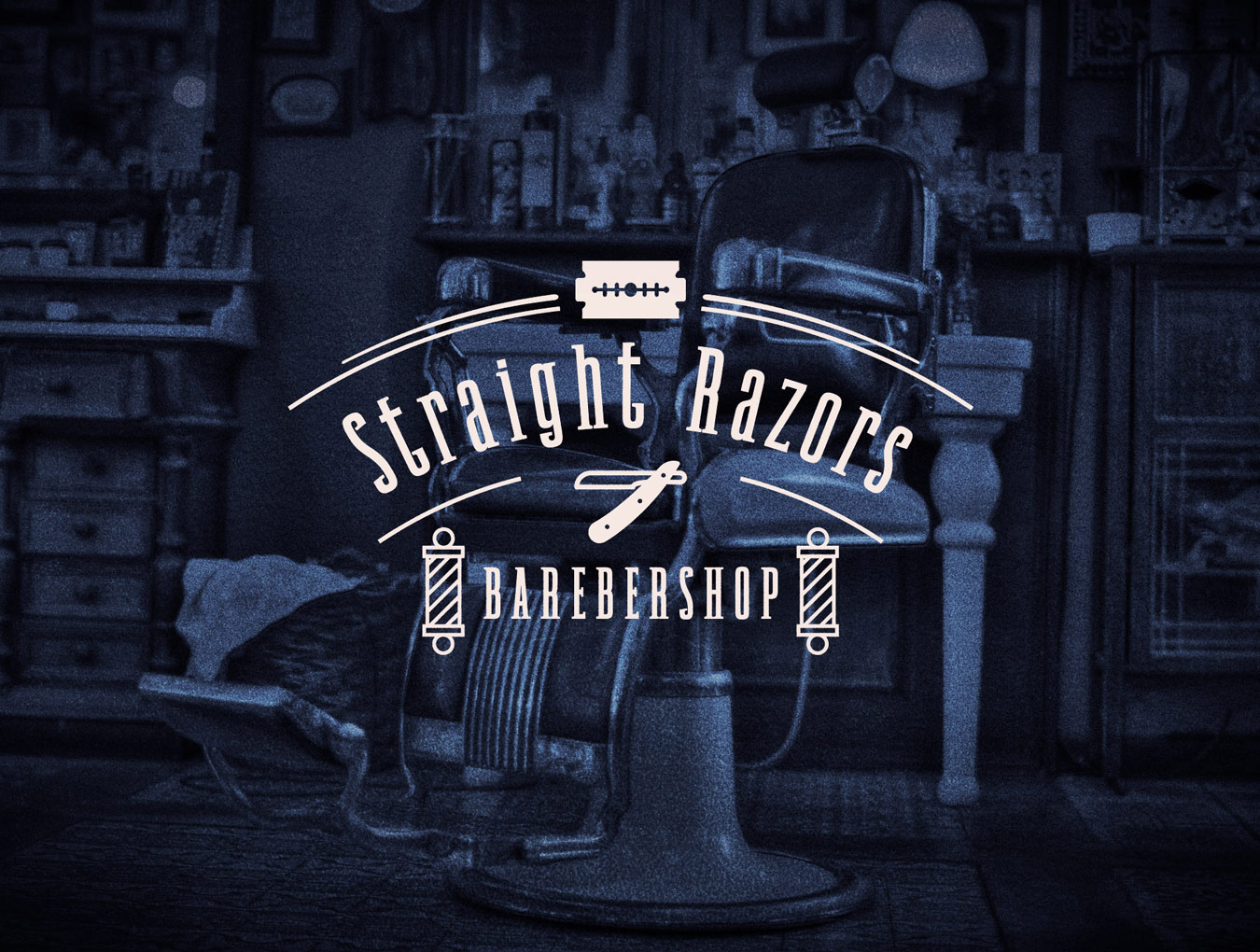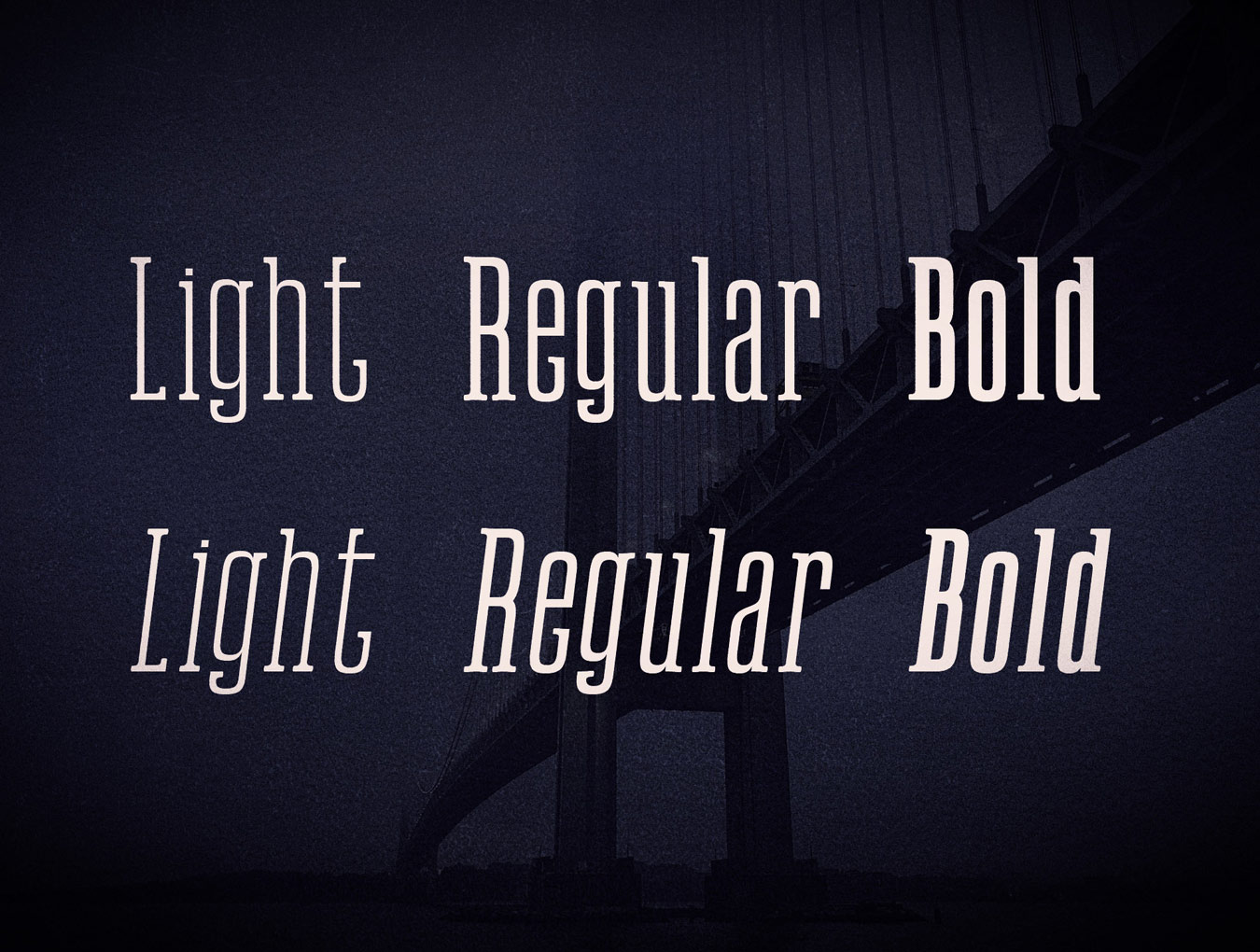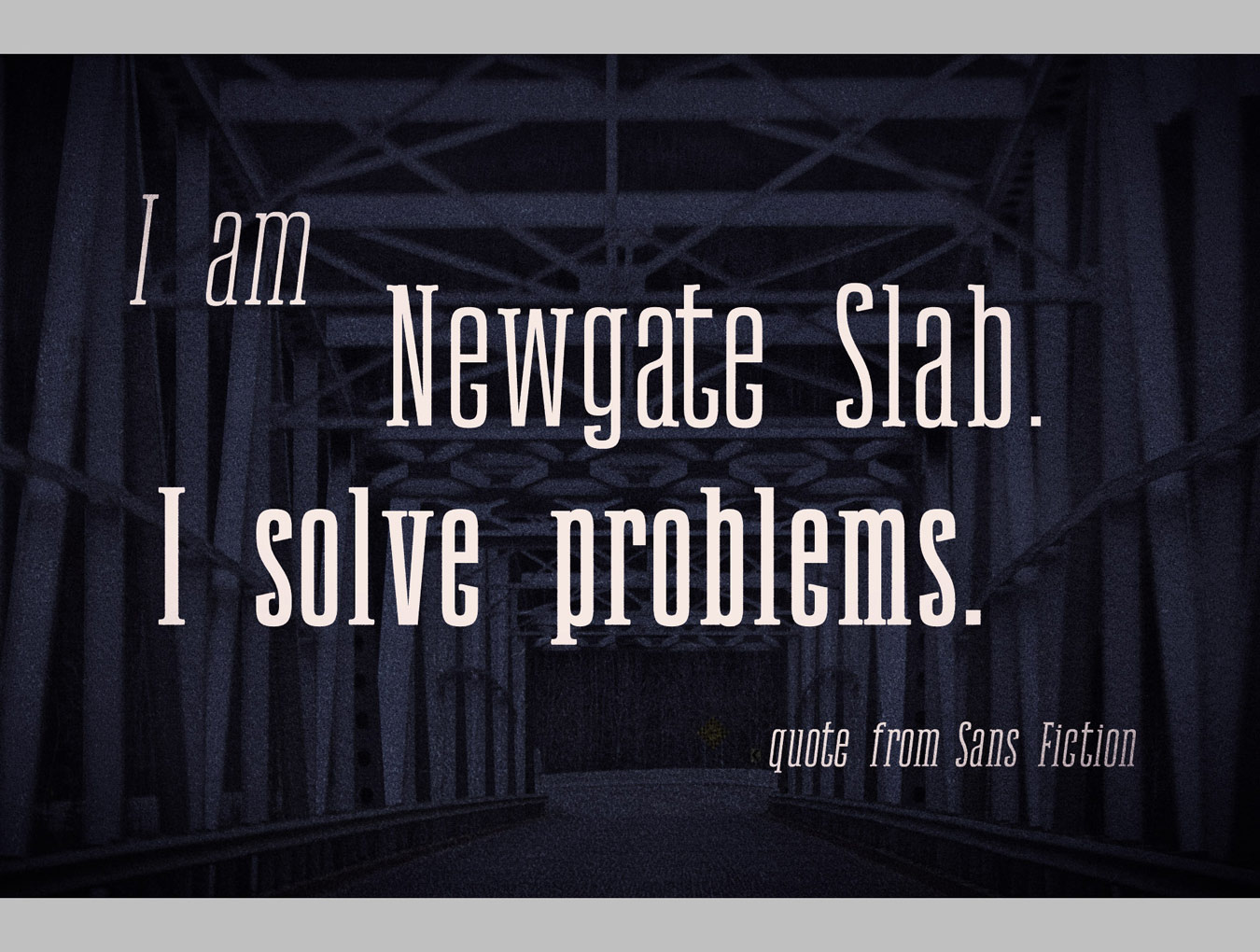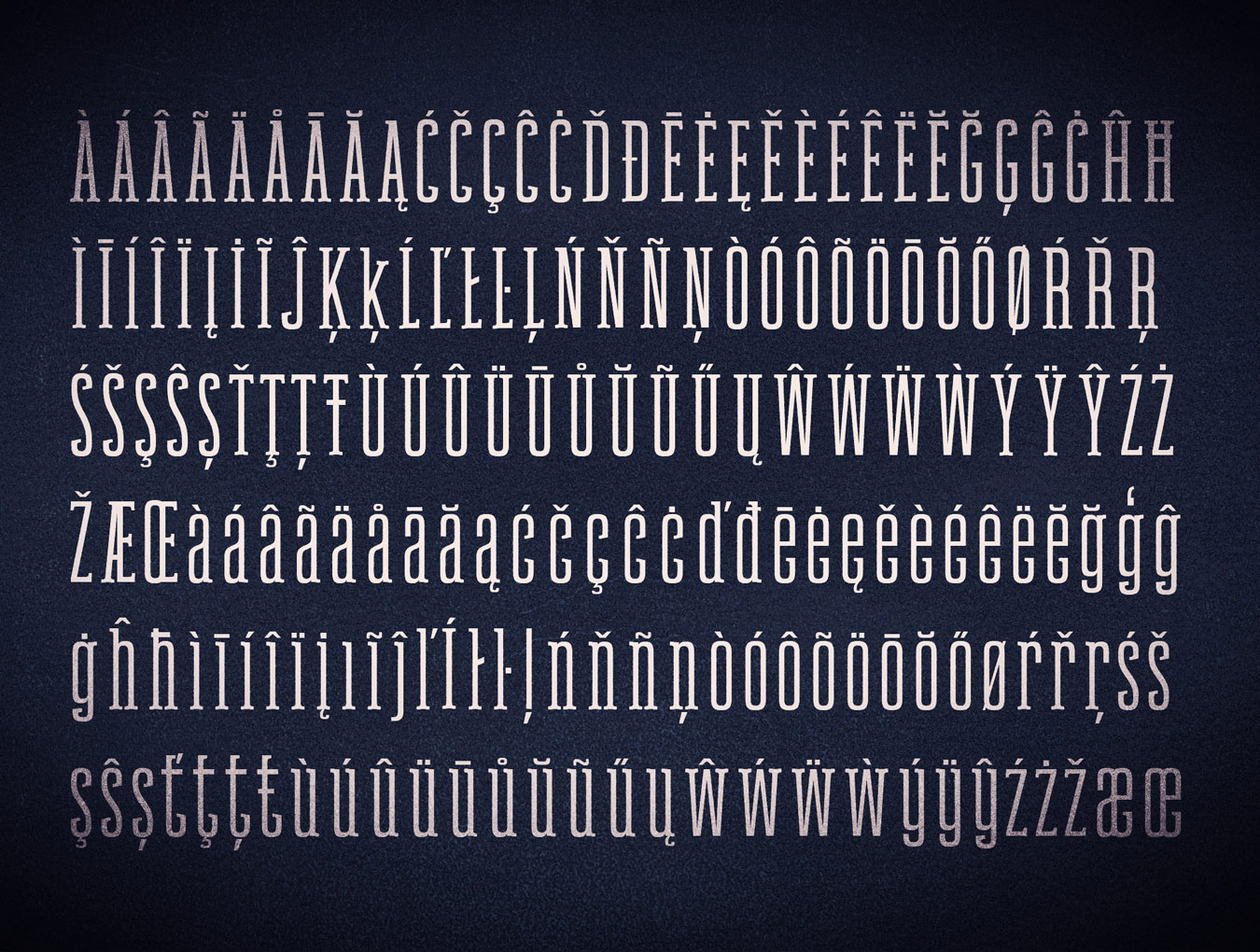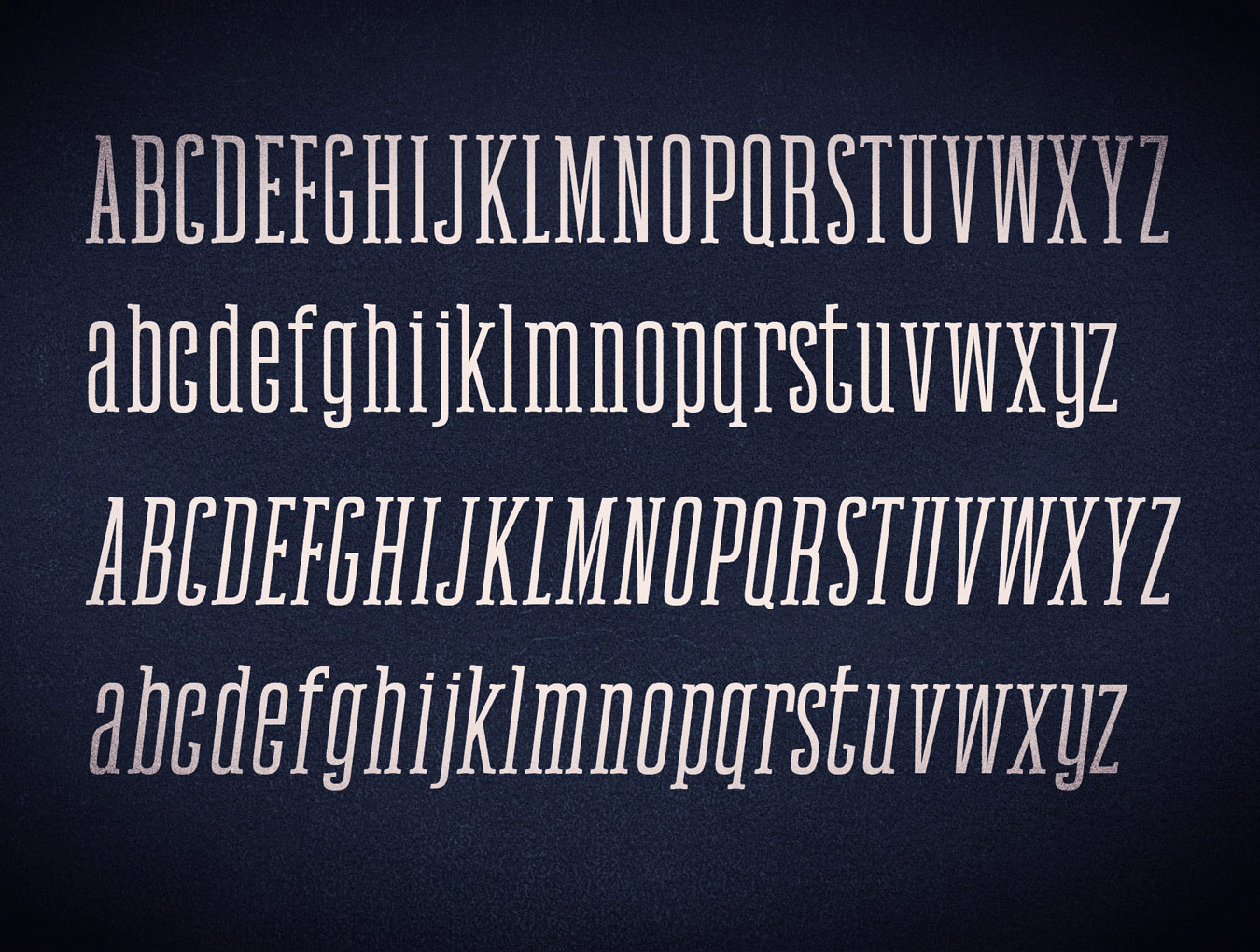
一种现代浓缩的字体,带有复古感。Newgate Slab
Newgate是现代浓缩字体与复古的感觉。 它旨在作出声明,非常适合标题,标识,品牌材料,海报等。 Newgate Sans字体包含六种字体:浅色,斜光,正规,常规斜纹,粗体和粗斜纹。所有提供广泛的语言支持,大小写,数字和扩展标点符号。 它有每种风格330个字形 - 涵盖西方和中欧拉丁语系的语言,如英语,法语,德语,波兰语,拉脱维亚语,罗马尼亚语和土耳其语等等。